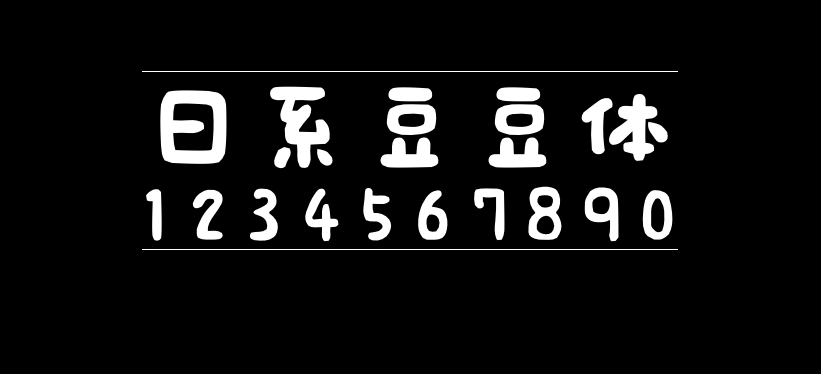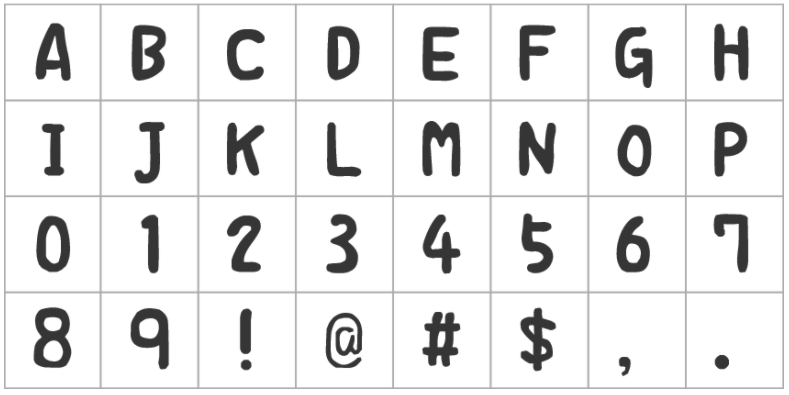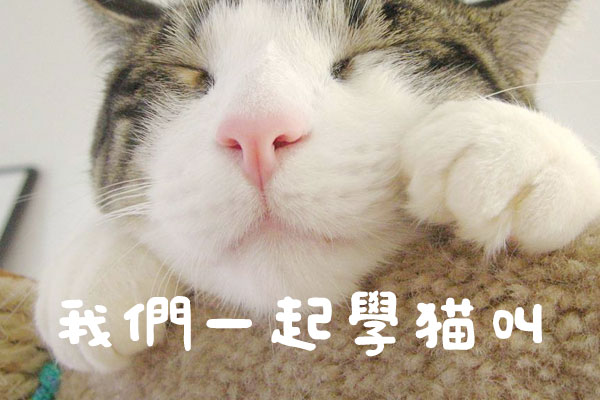
日系豆豆体
日系豆豆体(えるまー ElmerFont)就像用魔法笔写的手写字体。字体的风格圆滚滚的,就像豆豆一样可爱,特别适合用于女性,婴儿,儿童,偏可爱风格的海报设计。可以作为标题文字和印刷物等的素材使用。这款字体虽然发布的时间比较久远,最早发布于2006年,但是字体却是永不过时的。这款字体是日本的设计师发布的字体,所以字符是以JIS为标准的,所以对繁体支持较好,简体字相对少一些。
マジックペンで書いたような手書きフォントです。<第二水準まで>
バナー文字や印刷物などの素材としてご使用いただけます。
足跡やハート等が罫線の後半に入っています。「けいせん」を変換させてみてください。